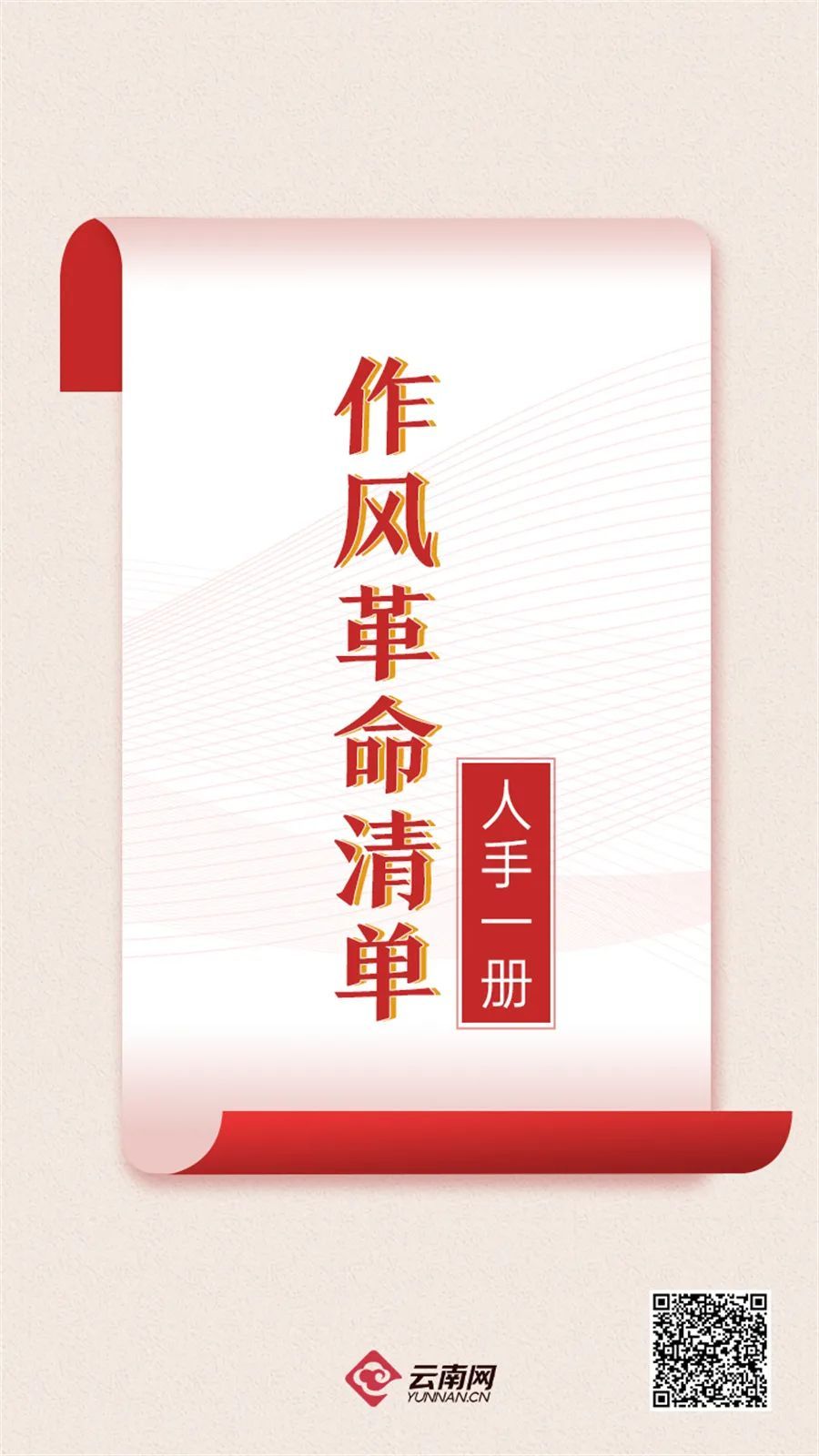
方正FW筑紫古典L黑
Fontworks,方正字库
黑体
这是筑紫字体黑体系列中文字比例最优美的一款字体的大字风格。筑紫古典黑体的每个字都是依照汉字固有的造型和骨架,用生动的风格绘制而成的。另外,手写般的假名能让人联想起运笔方式,并将汉字本身所具有的表情做得更加丰富。这款字是为数不多的、既继承了金属活字和照排文字的传统,又融合了古典恬静幽雅和现代新颖的一款黑体。此款是排版时具有现代感字距的「大字风格」。